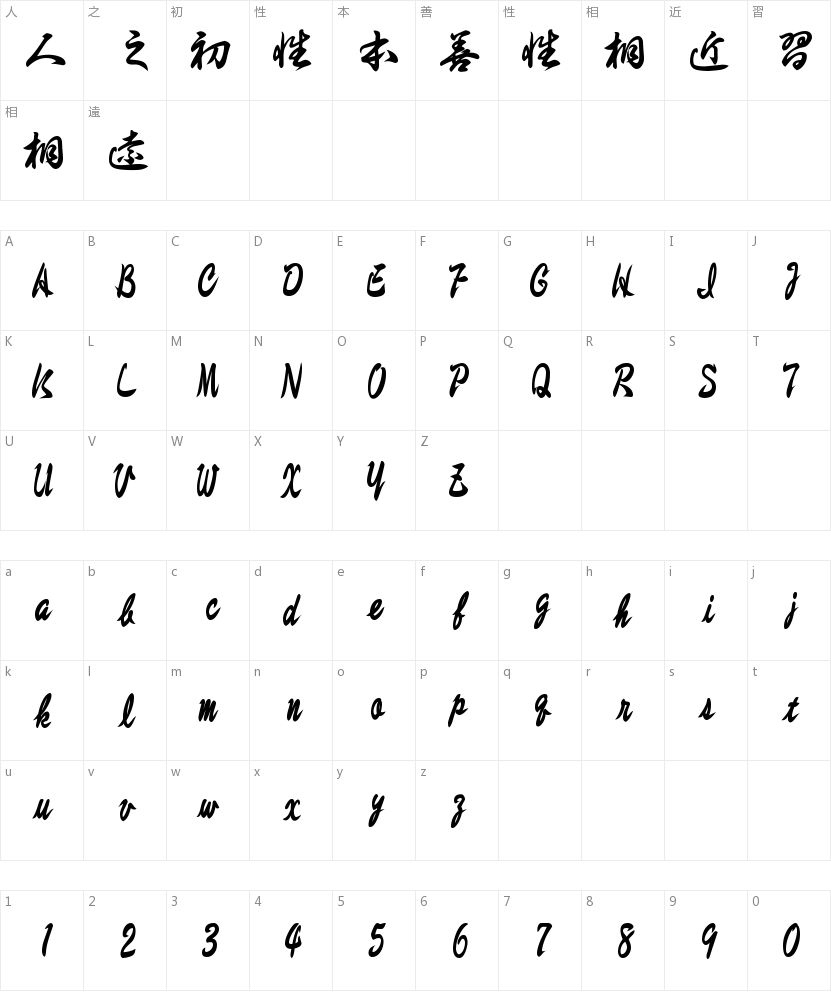
? 方圆太极草书是一种汉字字体,它以太极图为原型,以汉字书写形式表达,结合了太极八卦图案的笔画,融合了中国传统文化美学,在笔画结构上运用了太极图的拳脚动作,又充分考虑到汉字书写的美观性。它给人以安静、淡雅、稳重的感觉,体现出中国传统文化的深厚底蕴。文件名:FangYuanTaiJiCaoShu-2.ttf
方圆太极草书是一款非常不错的手写艺术字体,具有很好的视觉感,适合于文化类的宣传设计、商业类品牌的广告和产品包装设计以及个性化文字排版等较多场景。